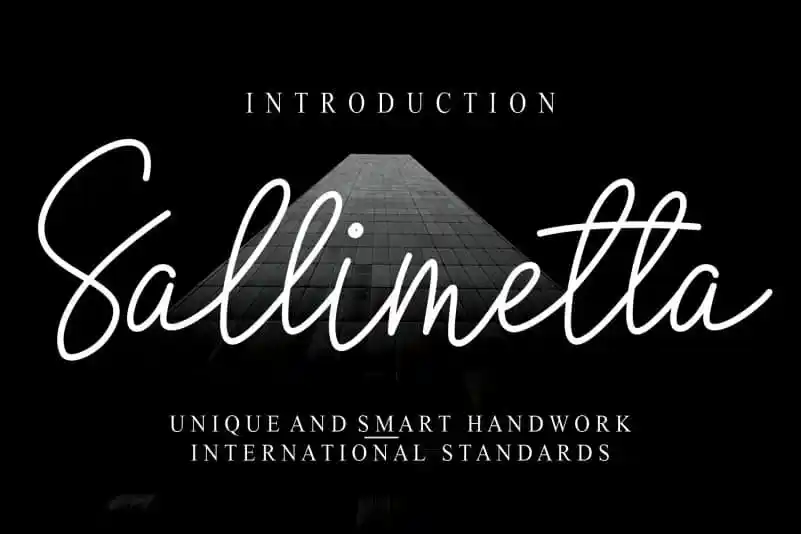
Sallimetta Script Font – Download Grátis
A Sallimetta Script Font é uma mão-desa elaborada que captura a essência do desenho artesanal, perfeita para quem busca expressar elegância e delicadeza em seu design gráfico. Com uma aparência suave e sofisticada, esta fonte traz uma atmosfera envolvente e natural ao seu trabalho. Ela não só adicionará um toque de autenticidade à sua tipografia, mas também dará vida a cada palavra que ela encarne. Adaptável para uso em diversas aplicações – desde anúncios até cartões personalizados – essa fonte é uma escolha perfeita para quem valoriza a arte da escrita manuscrita e busca dar um toque único ao seu trabalho visual. Ideal para designers que buscam um elemento de diferença em seus projetos, a Sallimetta Script Font é uma ótima opção para aqueles que valorizam o charme das fontes criadas à mão.